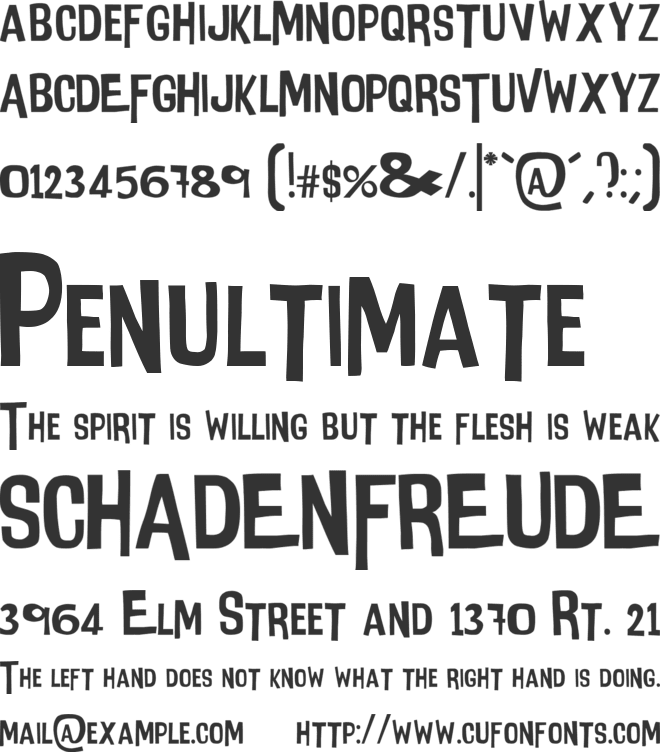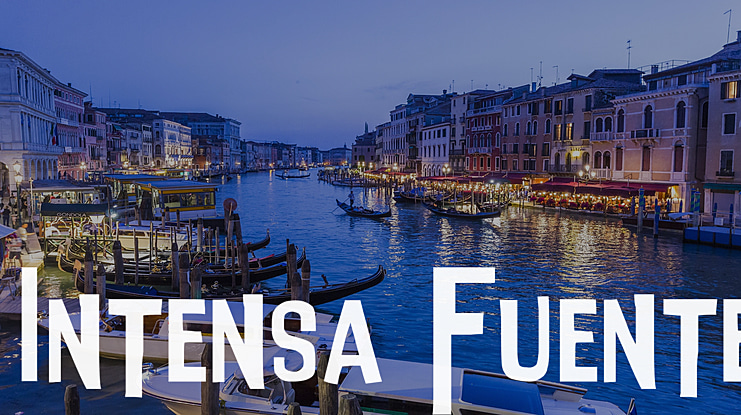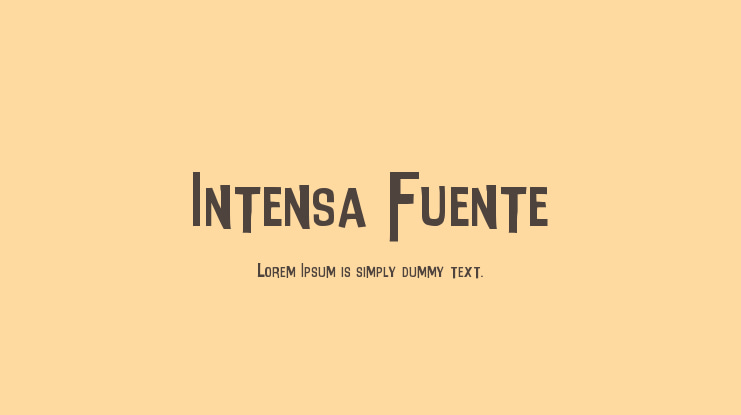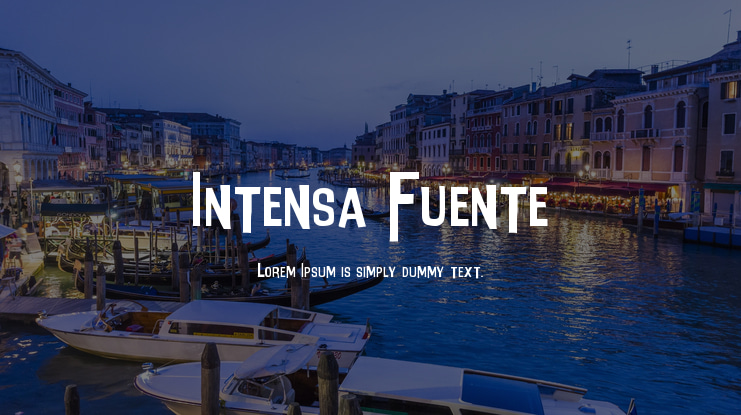
Intensa Fuente Font
Esta es mi fuente preferida ya que yo la hice a la edad de 12 años, está basada en la película "Inside out" o como la conocen en Latinoamérica "Intensa mente", si quieres felicitarme, burlarte de mi o simplemente pedirme unos caracteres específicos, por favor déjame un comentario sobre lo que piensas, con gusto te atenderé, hablo Español e Inglés.
This is my favourite Font because i did it when I was 12 years old, it's based on the film "Inside out" or "Intensa mente" here in Latin America, if you want to congratulate me, make fun of me or just ask me for some specific characters, please leave me a coment about what do you think, I will attend you, I speak English and Spanish.